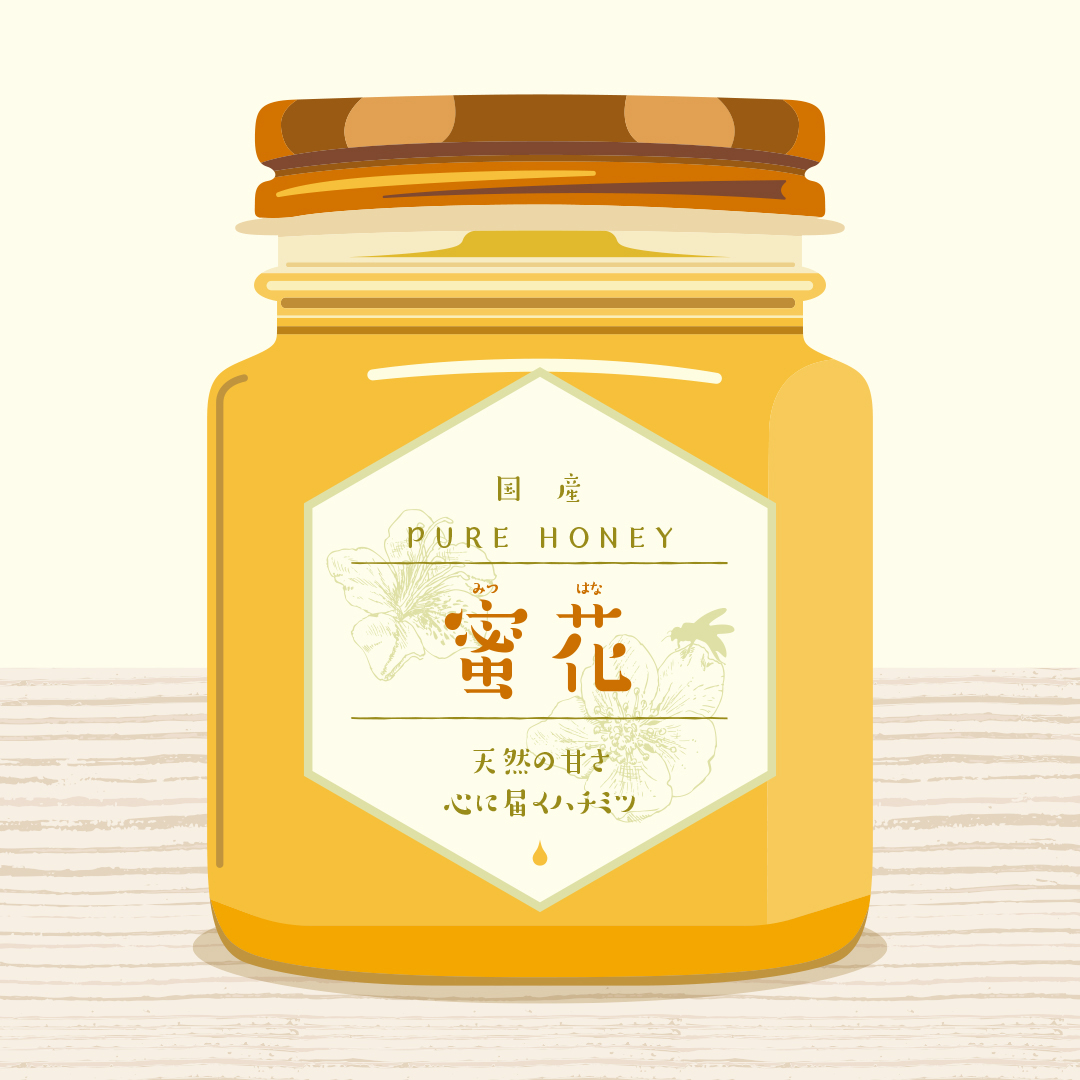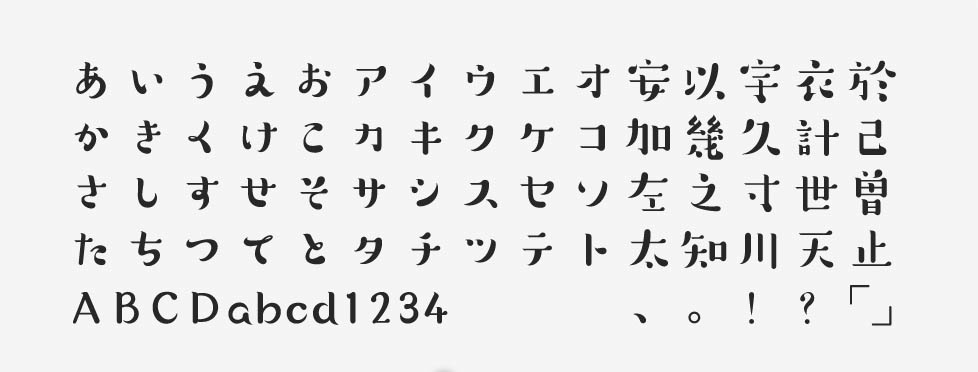
「すずむし」について
すずむしは、モリサワによる「タイプデザインコンペティション 2012」の和文部門で3つの賞(モリサワ賞 銅賞/明石賞/ファン投票1位)を受賞したデザイン書体です。2014年にモリサワの新書体として製品リリースされました。江戸落語や小噺のような人情味あふれた世界観で制作されています。
「すずむし」の特徴
特にかな文字が柔らかなすずむしは、ポップで可愛らしい雰囲気を携えています。個性が強く、あえてバランスを崩すことが重視されているデザインです。文字列に動きを加えてリズムを生み出すことができます。
可愛さを感じさせる主なポイントは、字面のサイズ感やふくよかな点画です。字面は小さめに設計されていて、正方形の型にはめずに整えすぎないようにデザインされています。点画は墨をたっぷりと含ませた筆で書いたような瑞々しい佇まいです。
はちみつの商品ラベルの作例で使用したすずむしは、テキストを打ち出すだけでオリジナルのロゴデザインができてしまったような特殊な雰囲気を持っています。個性的で親しみを感じる愛らしい造形です。フォント名も秀逸ですね。